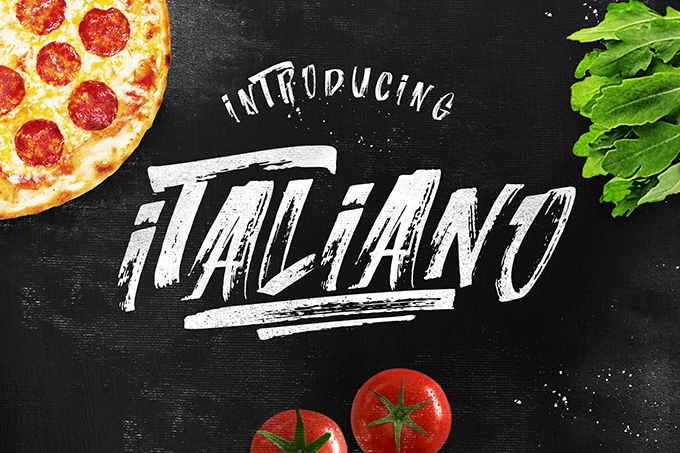
Italiano Brush Font – Download Grátis
Italiano Brush Font é uma excelente opção para designers que buscam expressar personalidade com os textos. Embora seja uma fonte script, sua natureza agressiva e vibrante faz dela perfeita para criar mensagens impactantes. Com um estilo brush, Italiano inclui todos os caracteres gerais da Europa Central, oferecendo versões em reta e inclinada. Suas linhas fluidas e traços bruscos criam uma aparência que se assemelha a letras escritas a mão, fazendo-a ideal para criar mensagens chamativas ou logos. Ideal tanto para nome tags quanto para aplicativos de mídia social, o Italiano Brush é perfeito para aqueles que querem adicionar um toque único e autêntico às suas criações. Seja para embalagens de produtos, materiais de merchandising ou até mesmo camisas personalizadas, a sua versão script garante uma imagem memorável e única. Além disso, seu design é tão interessante quanto eficaz, fazendo-o uma fonte perfeita para criar cartões de aniversário customizados também.